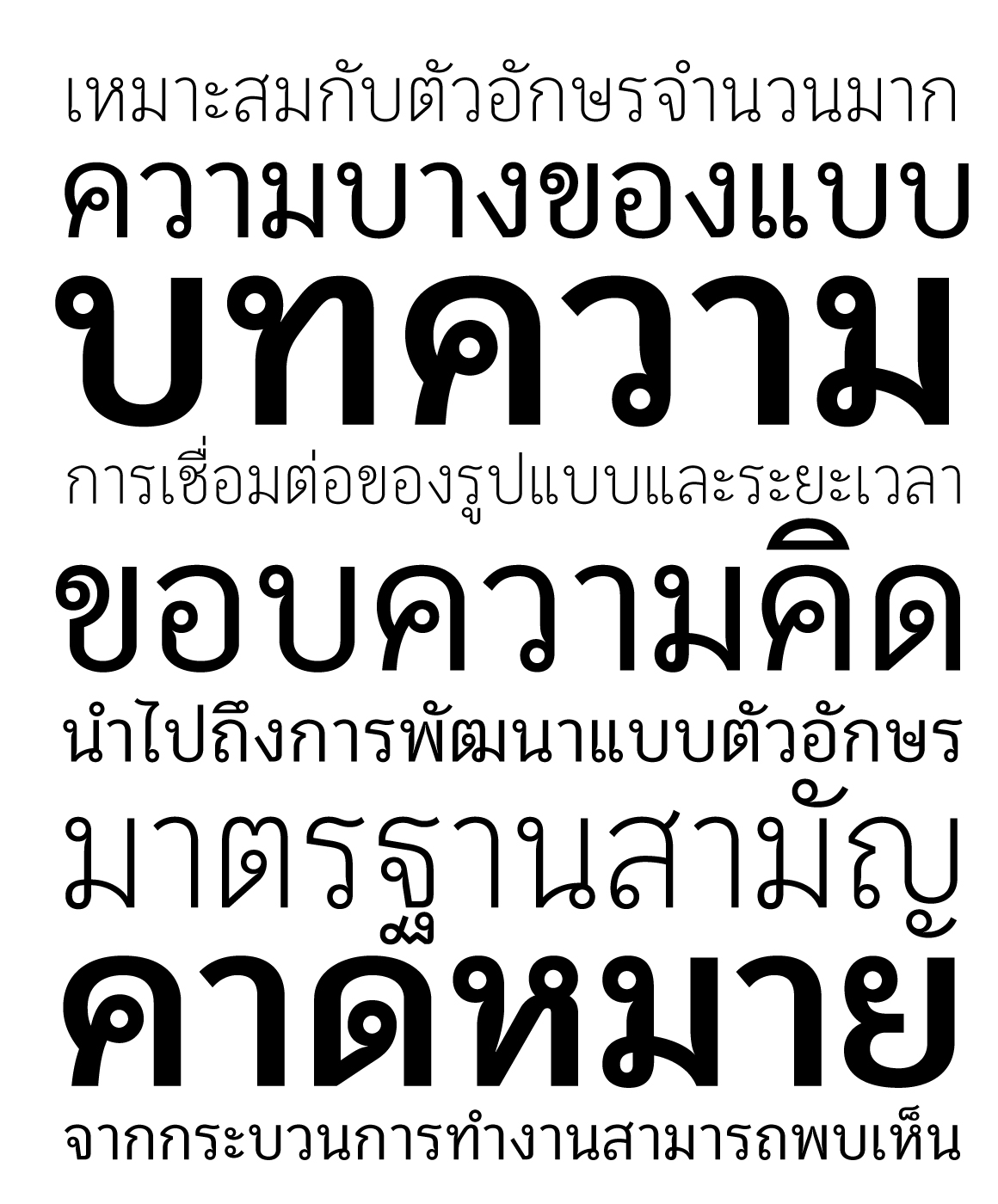
Muttayat
Muttayat™ (มัธยัสถ์) แบบตัวอักษรหัวกลมที่ผ่านการวิจัย “การออกแบบตัวพิมพ์เพื่อช่วยลดต้นทุนและวัตถุดิบในการพิมพ์” มาสู่การปรับโครงสร้างและรูปแบบแบบให้ดูร่วมสมัยเข้ากับบริบทในปัจจุบัน พร้อมทั้งขยายน้ำหนักเพื่อตอบสนองรองรับการใช้งานที่หลากหลายยิ่งขึ้น Muttayat™ ได้รับรางวัลการันตีคุณภาพจากเวทีการประกวดตัวอักษรระดับโลกอย่าง Grashan ในหมวด Non-Latin ประจำปี 2014 รวมไปถึง รางวัล Good Design Award (G-mark) ประเทศญี่ปุ่น และ DEmark Award ของประเทศไทย ประจำปี 2013 อีกด้วย
Name : Muttayat
Weight : Light, Regular and Bold
Language : Latin 1 / Thai
Release Date : 2014
Designer :Thanarat Vachiruckul
Technician : Thanarat Vachiruckul
Award : DEmark Award 2013 / Good Design Award 2013 / Granshan Type Design Competition 2014